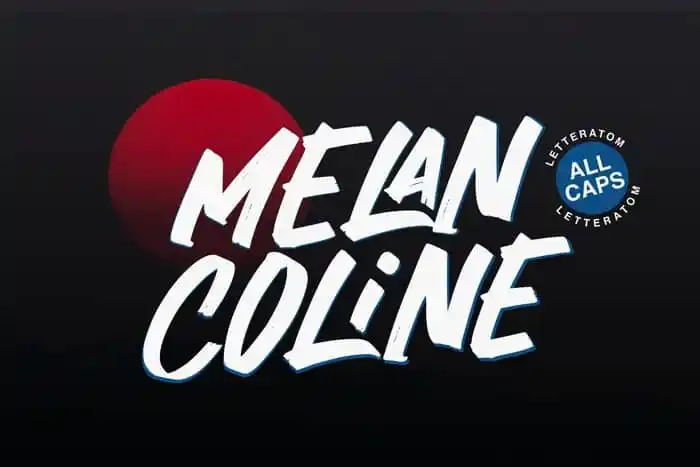
Melancoline Brush Font – Download Grátis
A fonte ‘Melancoline Brush Font’ é uma escolha perfeita para aqueles que buscam algo único e inovador no seu design. Originada do designer Letteratom, esta fonte é um tipo de display com estilo brush, criado a partir de técnicas manuais e rápida de traço, dando à sua escrita um aspecto confiante e forte. Obrigatórios em todas as palavras é o melancoline ligação LA LE LI LO LU LH, ideal para quem busca algo especial para seus projetos. Composta apenas de letras maiúsculas, esta fonte oferece uma impressão poderosa e convincente. O nome da font ‘Melancoline’ remete à sua natureza atemporal e reflexiva, perfeitamente adaptável a diversas aplicações gráficas. Para quem procura algo mais moderno e único em seu projeto de design, esta font é definitivamente o item perfeito no seu arsenal. Sem dúvidas, será uma escolha inteligente para qualquer designer que deseja dar um toque autêntico e pessoal a seus projetos digitais.